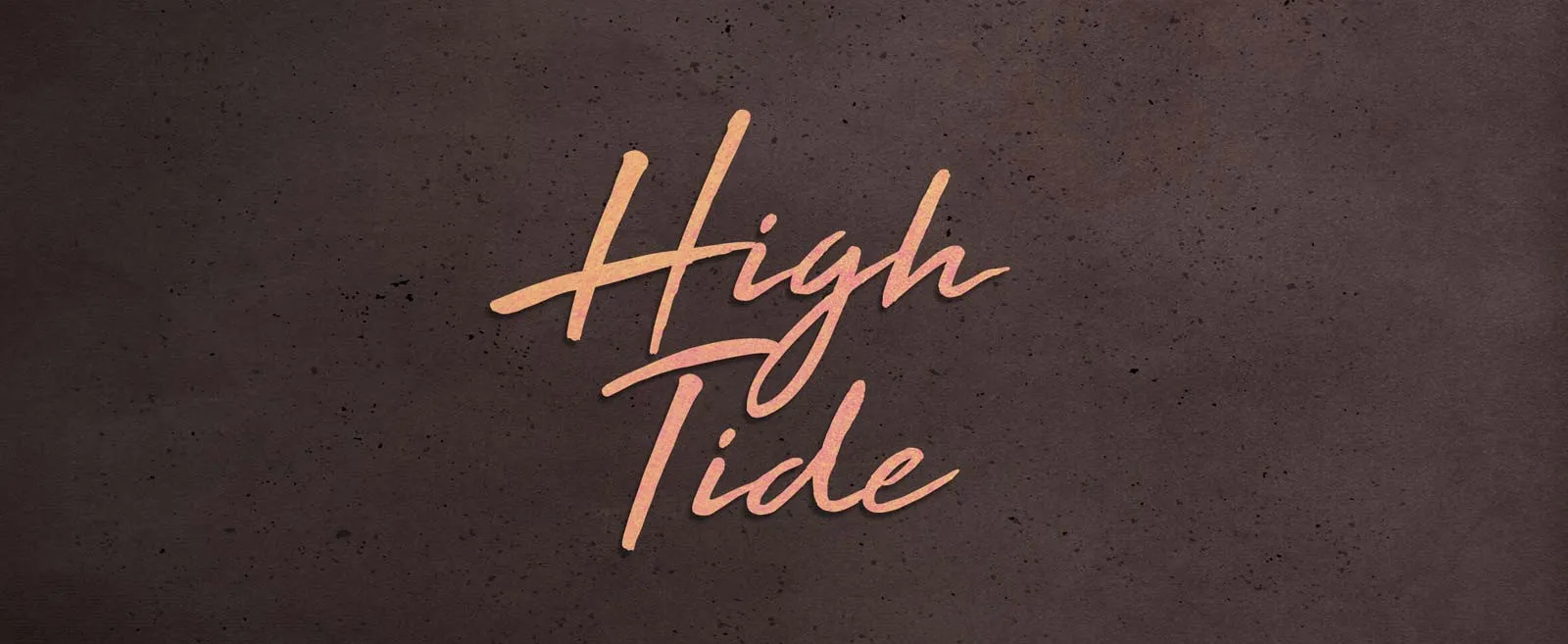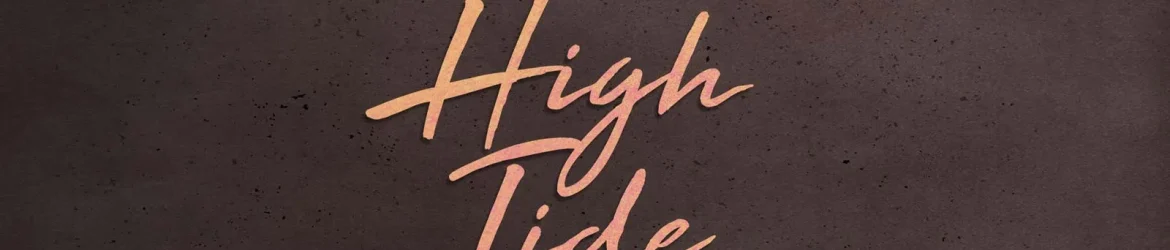
Introduzimos High Tide Font. Desenvolvida pelo designer blkbktyp, esta é uma fonte escrita a mão no estilo de calligrafia moderna. Ideal para criar materiais impressionantes de marca, belos logotipos, cartões, citações, convites de casamento, superposições e apresentações, High Tide oferece um estilo elegante e estiloso de caneta que certamente irá enriquecer qualquer projeto interessante. Seja para seus projetos digitais ou impressos, esta fonte escrita a mão em estilo moderno é uma escolha inteligente para quem busca um toque único e sofisticado.